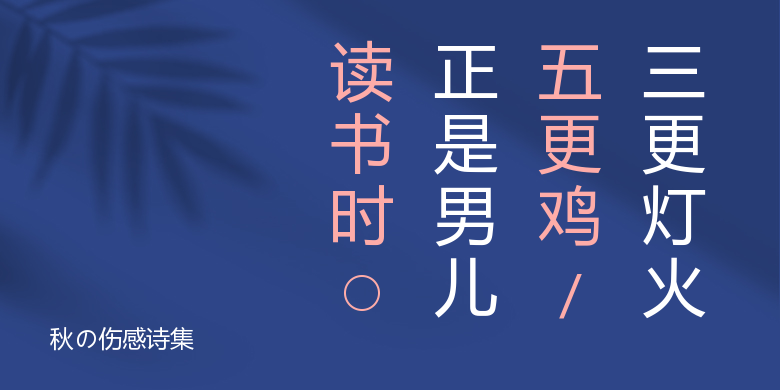
秋の伤感诗集
秋の伤感诗集,这款字体结构工整、笔画清晰,兼顾美观与易读性,适用于标题、正文、海报、包装、LOGO 等多种场景。字形优雅稳定,风格百搭耐看,适配日常排版与创意设计,让文字呈现更舒适、更具质感。秋の伤感诗集一笔一画,皆是细节,以均衡的比例、流畅的线条打造舒适视觉体验,字形端正大气,风格简约现代。无论是商业设计、品牌宣传还是日常排版,都能轻松驾驭,让文字更有格调与力量。秋の伤感诗集字体下载。